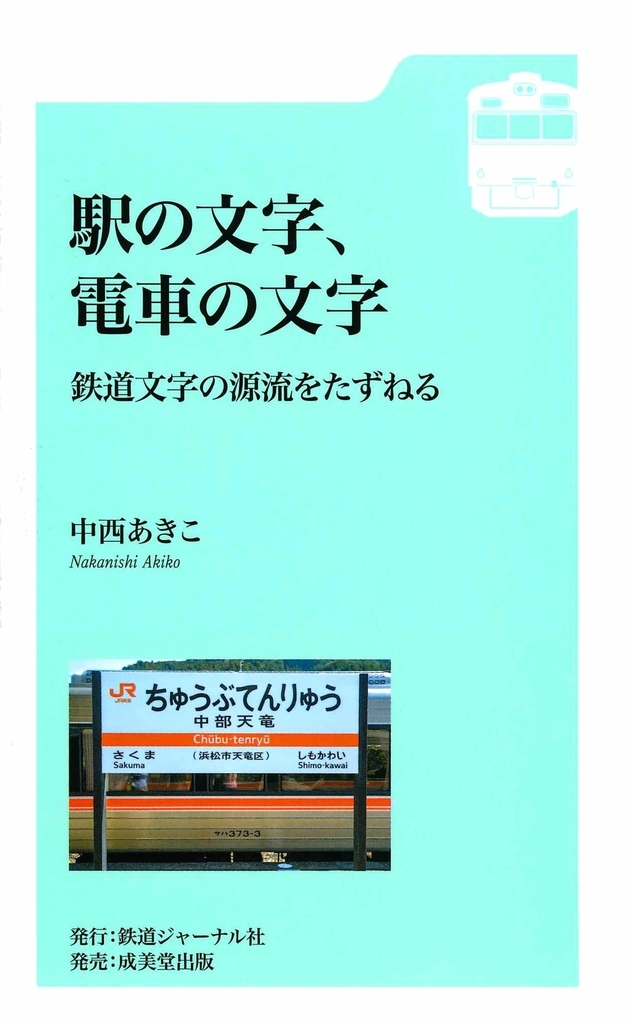
- 駅の文字、電車の文字 鉄道文字の源流をたずねる
中西あきこ氏著書「駅の文字、電車の文字 鉄道文字の源流をたずねる」が成美堂出版から2018年9月14日に発売された。
鉄道文字には旅客に向けたものと、現場の業務用に必要なもの、その二つの流れがある。もとより職員や職人の手書きという方法に拠ったので、具体的な書き方は細かく定める必要があった。
見やすく判読しやすいことは必要で、文字のかたちや大きさなども今日まで規程や図面によって指定されてきた。
そのことが鉄道文字に、市中に見られる一般の様々な文字とは異なる性格を与えてきた。
単なる記号でない鉄道文字の現状を通して、そこに秘めたサービスの心の真実をさぐる。
「されど鉄道文字」から2年。より深みへ。
中西あきこ氏Profile●1975年神奈川県生まれ。二松学舎大学大学院修了。大学時代より書道を学ぶ。月刊『旅と鉄道』(鉄道ジャーナル社)で地下鉄路線を地上でめぐる「二駅歩き」の連載をきっかけに地下鉄に残る旧い文字に興味を持つようになる。昭和の時代感覚あふれる看板や書体・フォントをたずねてさらに取材を続けている。
中西あきこ氏著書「されど鉄道文字―駅名標から広がる世界」
中西あきこ氏著書「駅の文字、電車の文字 鉄道文字の源流をたずねる 」は、鉄道ジャーナル社から2016年1月1日に発売。
鉄道ジャーナルが贈る知られざる鉄道物語。近代鉄道100年にわたる手書きのロマン。駅名標・車輛標記・ナンバープレート、鉄道文字の源流をたどる。